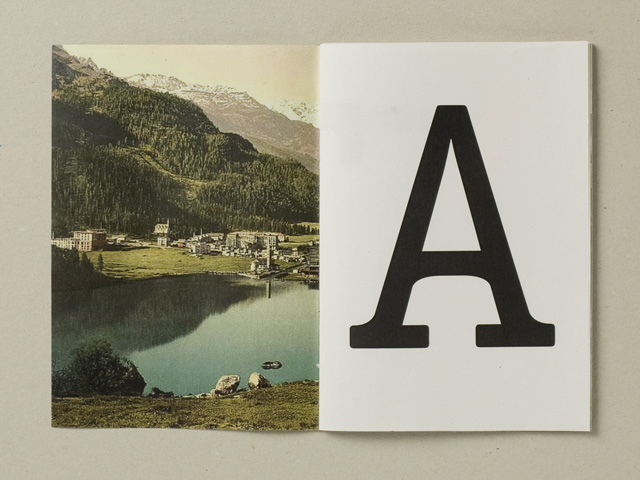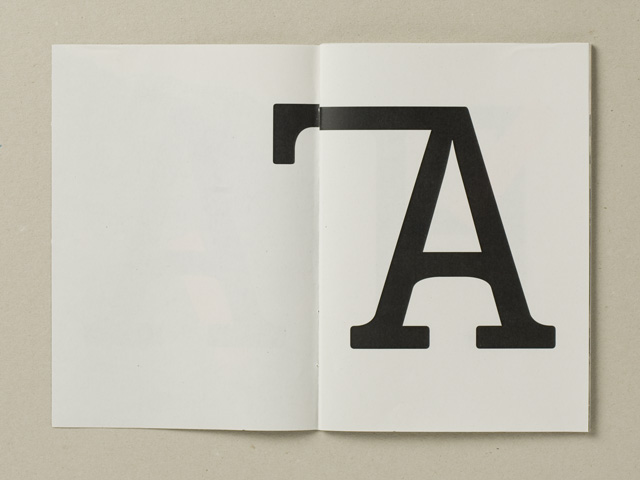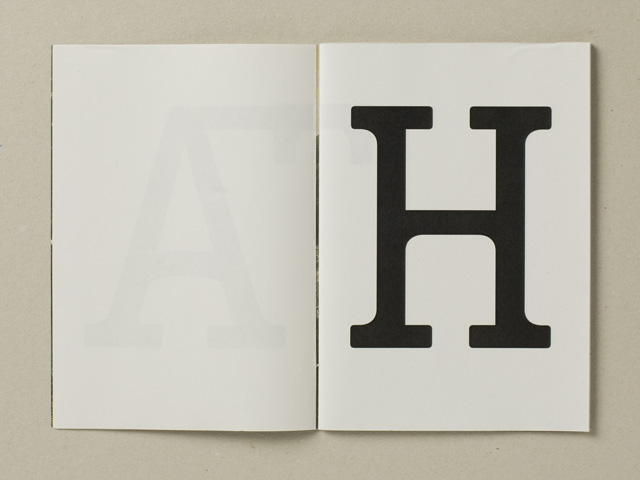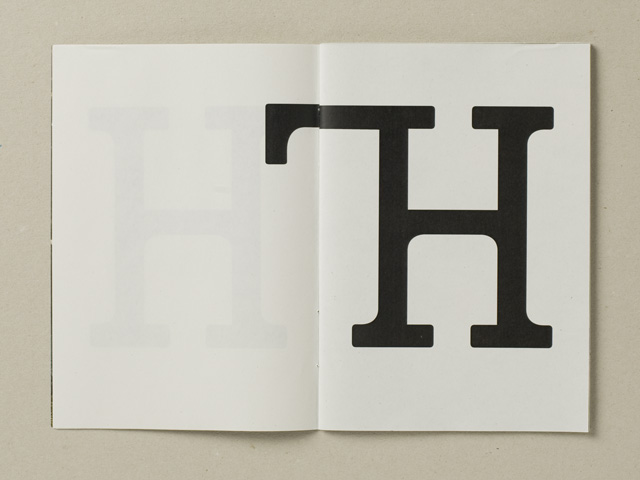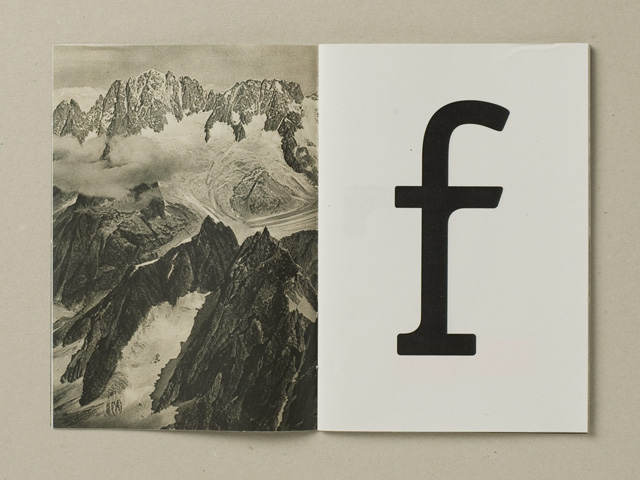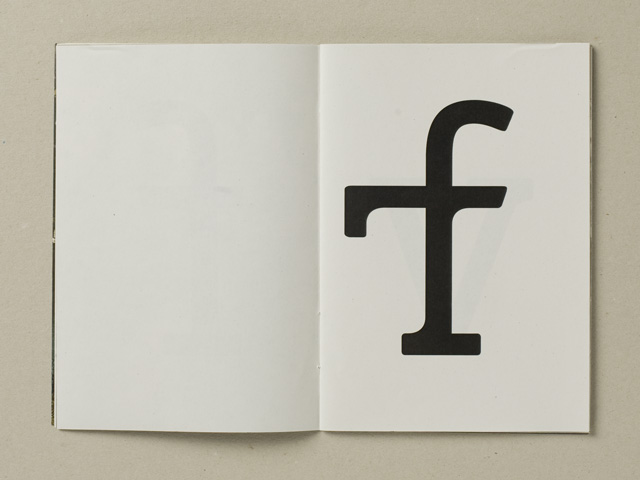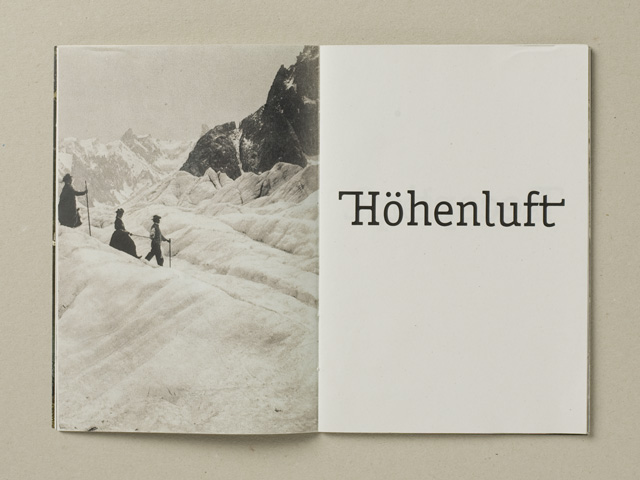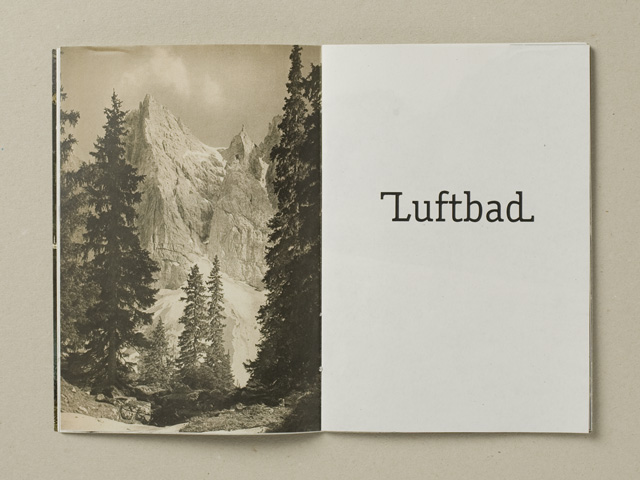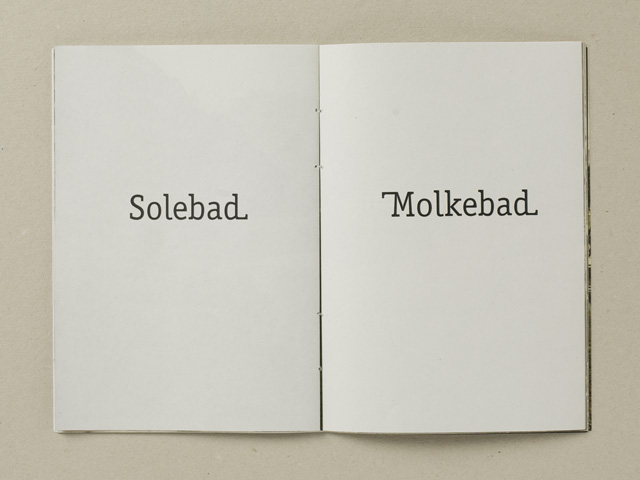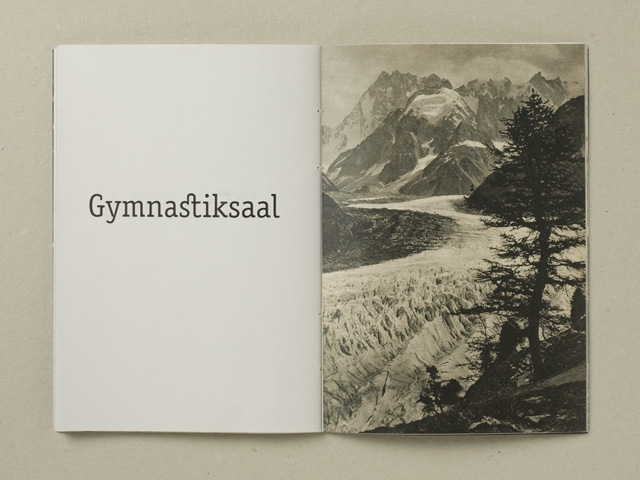
Sanatorium
Die Schrift eignet sich nicht nur für die wohlhabende Oberschicht und eine heilende Wirkung kann auch nicht garantiert werden. Sicher ist: Sanatorium hat eine schlichte und feine Anmutung, einen umfangreichen Satz an Swoshes und Ligaturen und nicht zuletzt schöne Details in der Strichführung.